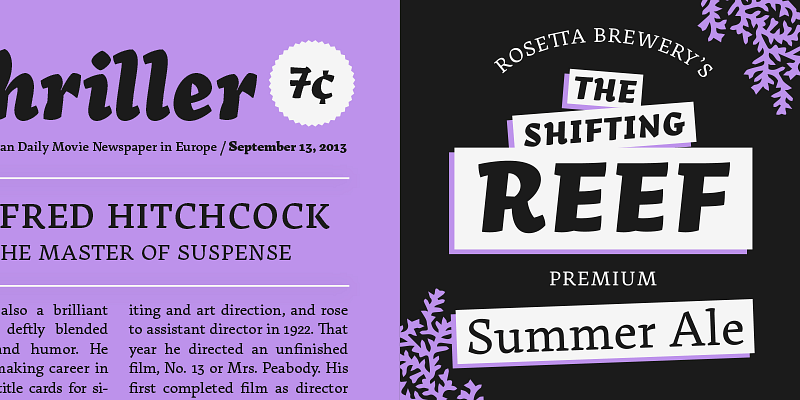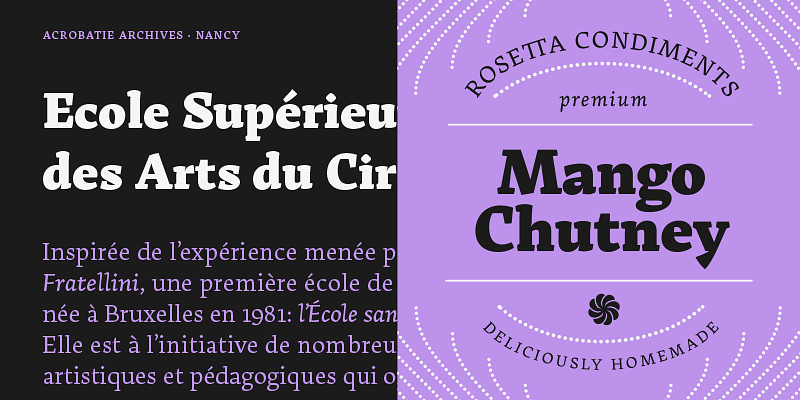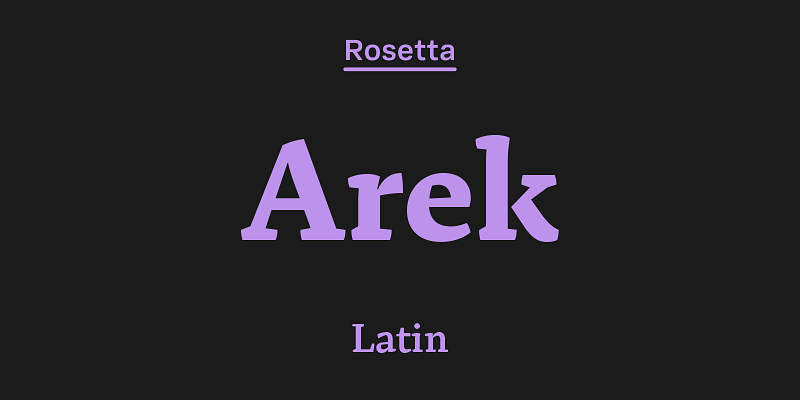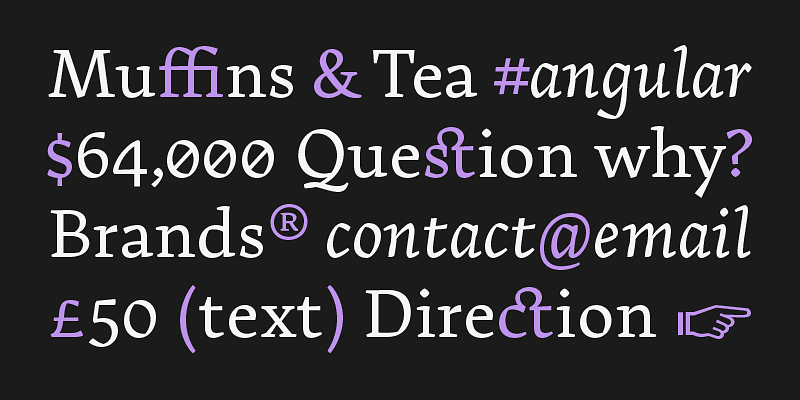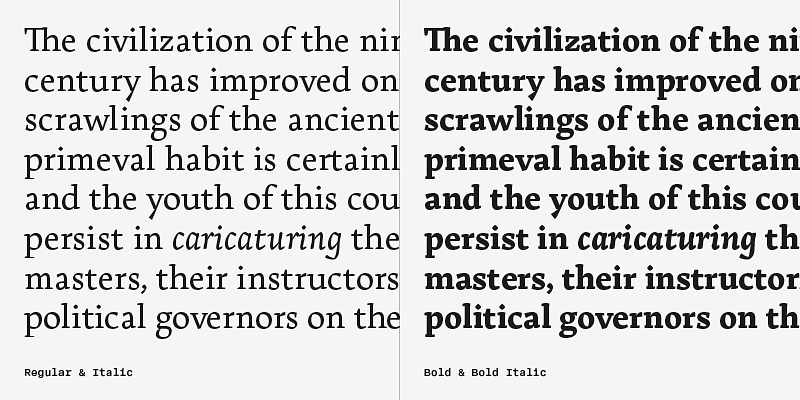
Un potente sistema di caratteri a più pesi che combina i caratteri verticali di chiara lettura con i corsivi cinetici in quattro pesi. Originariamente progettato per i libri scolastici, Arek è in grado di catturare l’attenzione di qualsiasi lettore e di gestire con facilità qualsiasi compito editoriale.